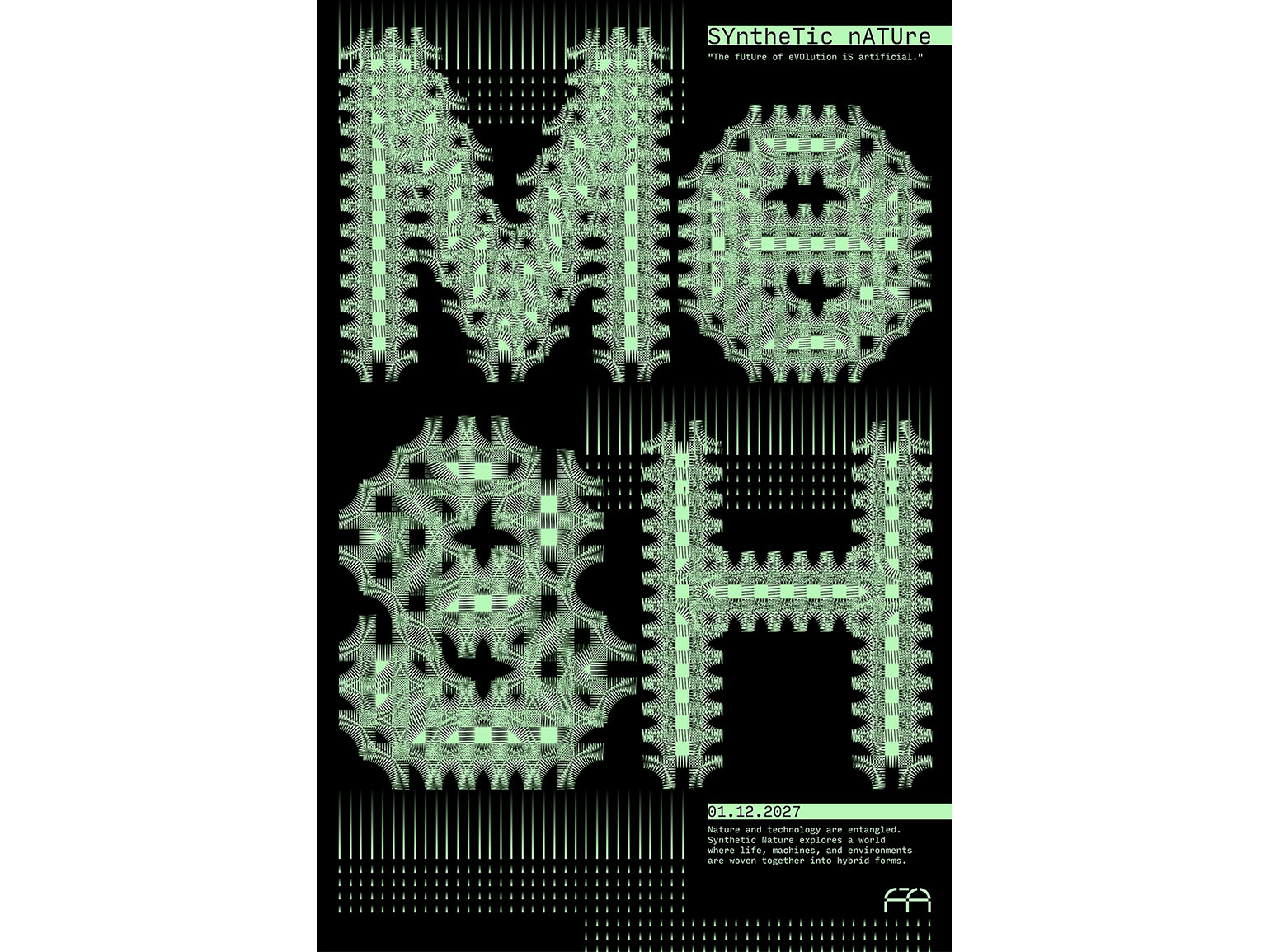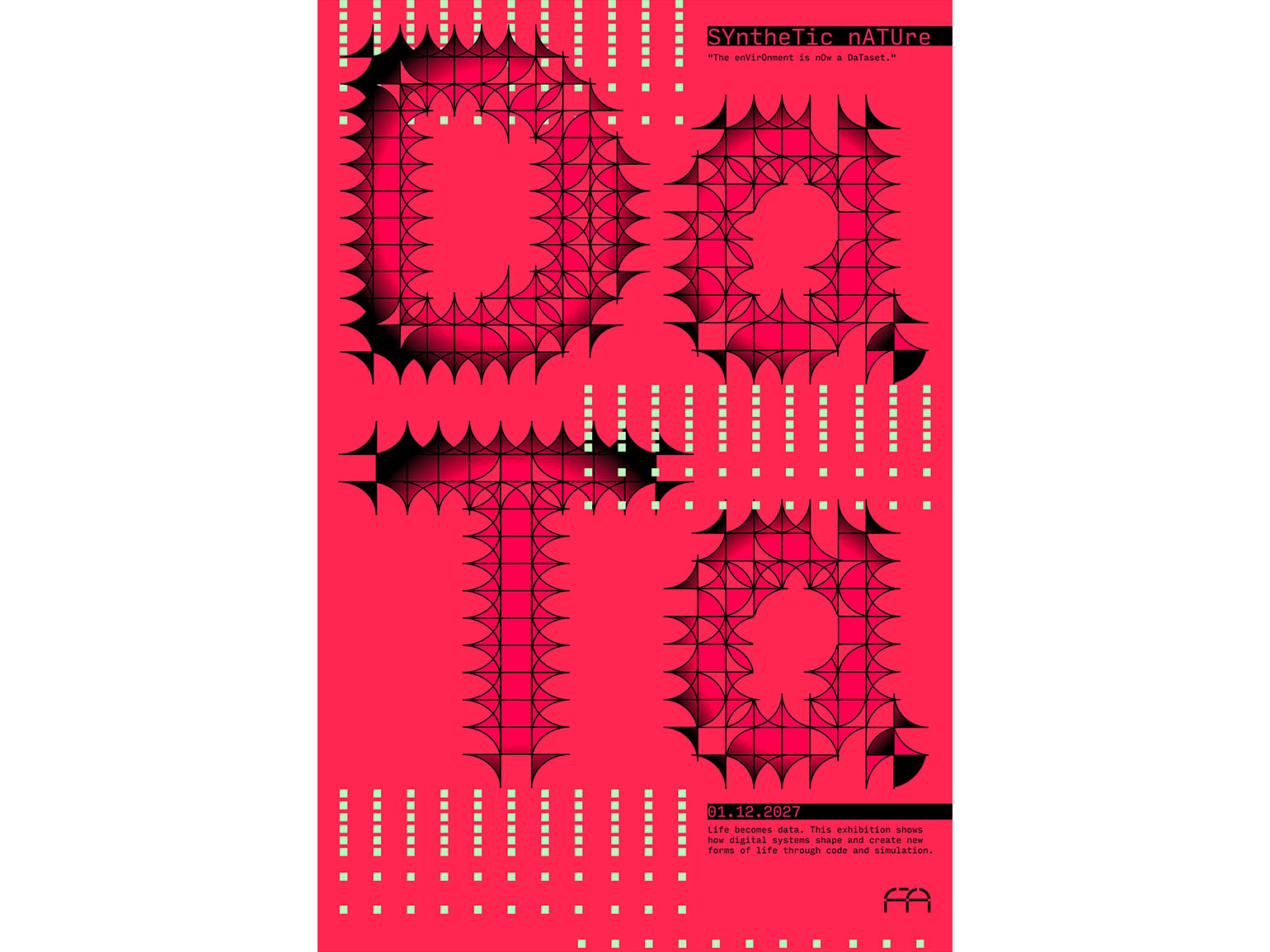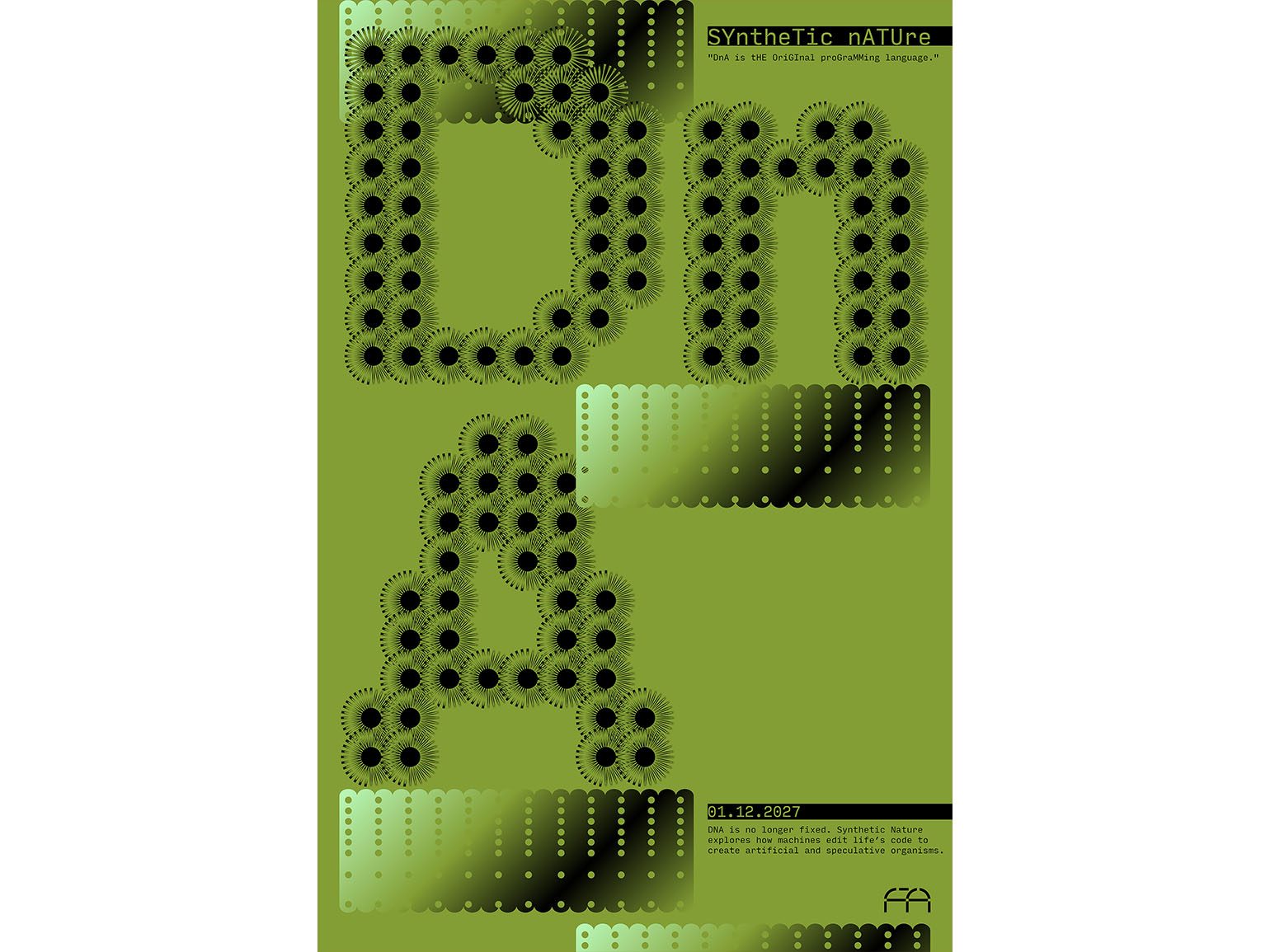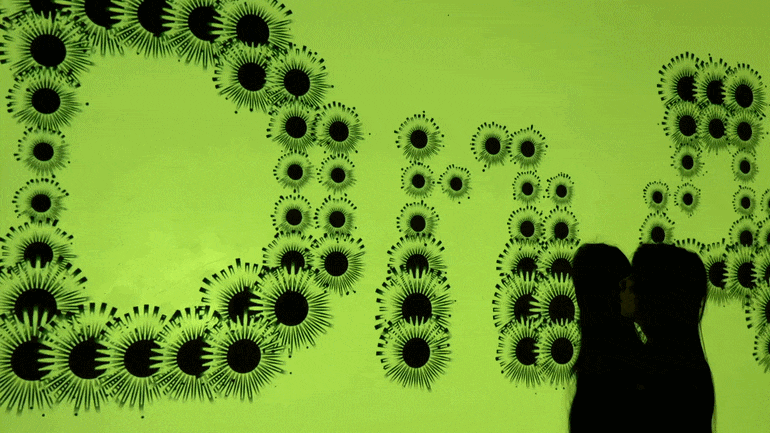
Дизайнер Элеанор Ян превратила шрифт в «живую систему»
К такой типографике можно прикоснуться.
Дизайнер Элеанор Ян выпустила проект Synthetic Nature — серию интерактивных шрифтов, которые реагируют на движения и прикосновения человека в реальном времени. В работе Ян соединяет графический дизайн, генеративную типографику и цифровые технологии. Она превращает буквы в динамическую среду, с которой можно буквально взаимодействовать с телом.
Проект построен вокруг идеи «живой типографики». Вместо статичных знаков получается система, которая меняется в зависимости от его действий. Шрифты реагируют на приближение, движение и тактильный контакт — например, через взаимодействие с материалами вроде травы или губки.
По словам Ян, задача проекта — показать, что цифровая среда уже не существует отдельно от физического мира. Алгоритмы, сенсоры и камеры встроены в повседневную реальность, а значит, визуальный язык тоже может выходить за пределы экрана. В Synthetic Nature экран перестаёт быть «окном» — он становится частью пространства, в котором находится пользователь.
Внутри проекта — три типографические системы, которые дизайнер описывает как «разные формы жизни». Одна из них построена по принципу ДНК и напоминает разветвляющиеся микроорганизмы, другая — более пористая и «тканевая», а третья — сложная сеть из проводов и узлов, отсылающая к цифровой инфраструктуре. Все они объединены идеей жизни на стыке биологии и вычислений.
Технически инсталляция работает в несколько этапов. Сначала система активируется при появлении человека — камера считывает лицо и расстояние до него, меняя поведение шрифта. Затем включается фаза эволюции: при прикосновении к физическим объектам параметры типографики — например, плотность или длина линий — начинают изменяться. Если пользователь уходит, то система постепенно возвращается в исходное состояние.
Для реализации проекта Ян использовала набор инструментов генеративной графики и 3D-дизайна, включая p5.js, Cavalry, Spark AR и Cinema 4D, и объединила их в единую экосистему.